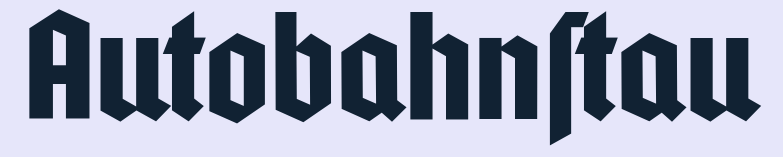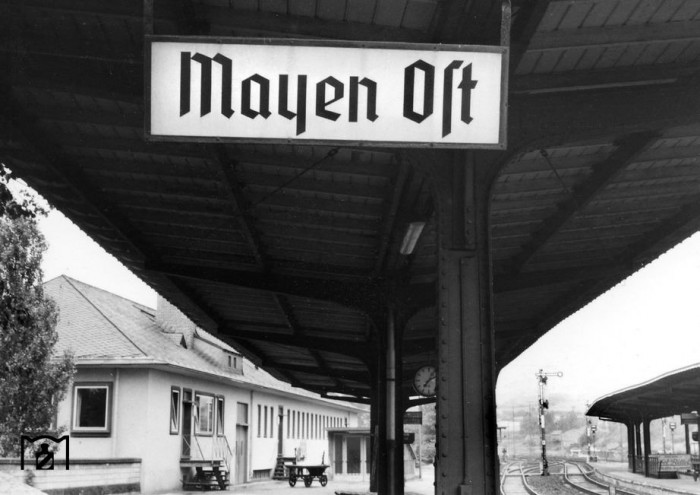
Bahnhofsschrift
weiß Jemand, wie diese Schrift heißt oder wo man sie so oder ähnlich runter laden kann?
also genau kommen die alle nicht:
bis auf Blankenburg haben die kein langes "S"
also genau kommen die alle nicht:
Was daran liegt, dass damals Schilder nicht mit Satzschriften gesetzt wurden. Ging ja auch technisch gar nicht. Schilder wurden (in aller Regel) vom Schildermaler gezeichnet.
Mehr Schriften dieses Stils sowie Hinweise auf Digitalisierungen haben wir hier:
also genau kommen die alle nicht:
bis auf Blankenburg haben die kein langes "S"
Die Autobahn hat es, nur eben in der korrekten Unicode-Position:
Aber sag mal, catfonts, auf welche Vorlage hast du dich bei der Zeichnung der Blankenburg eigentlich gestützt? Du erwähnst die Tannenberg, aber einige Formen unterscheiden sich dann doch deutlich von den Vorlagen, die z.B. unser Wiki von der Blei-Tannenberg zeigt. Gab es einen solchen Tannenberg-Schnitt?
Ach so, die für Blankenburg digitalisierte Vorlage war ein Hamburger Museumskatalog aus den 50ern. Welche Schriftart hier verwendet wurde - möglicherweise ja auch von einer Hamburger Schriftgießerei, entzieht sich leider meinem Wissen.
Aber sag mal, catfonts, auf welche Vorlage hast du dich bei der Zeichnung der Blankenburg eigentlich gestützt? Du erwähnst die Tannenberg, aber einige Formen unterscheiden sich dann doch deutlich von den Vorlagen, die z.B. unser Wiki von der Blei-Tannenberg zeigt.
Ach so, die für Blankenburg digitalisierte Vorlage war ein Hamburger Museumskatalog aus den 50ern. Welche Schriftart hier verwendet wurde - möglicherweise ja auch von einer Hamburger Schriftgießerei, entzieht sich leider meinem Wissen.
Von den charakteristischen Formen wie EeKkM etc. her zu urteilen war die Vorlage keine Tannenberg, sondern ein Schnitt der Potsdam. Also in der Tat das Produkt einer Hamburger Schriftgießerei (Trennert).
Danke. Das hatte ich mir schon gedacht. Allerdings hab ich es dann einfach bei der Vermutung belassen, da die "Schaftstifler" hinreichend ähnlich zueinander sind, und ich beim Vergleich verschiedener Bahnhofsanschriften deutliche Unterschiede zwischen den Werken der Schildermaler gesehen hatte. In so fern macht es nichts, wenn da eine Tannenberg empfohlen wurde, und dann doch dem Schildermaler eine andere als Muster diente.